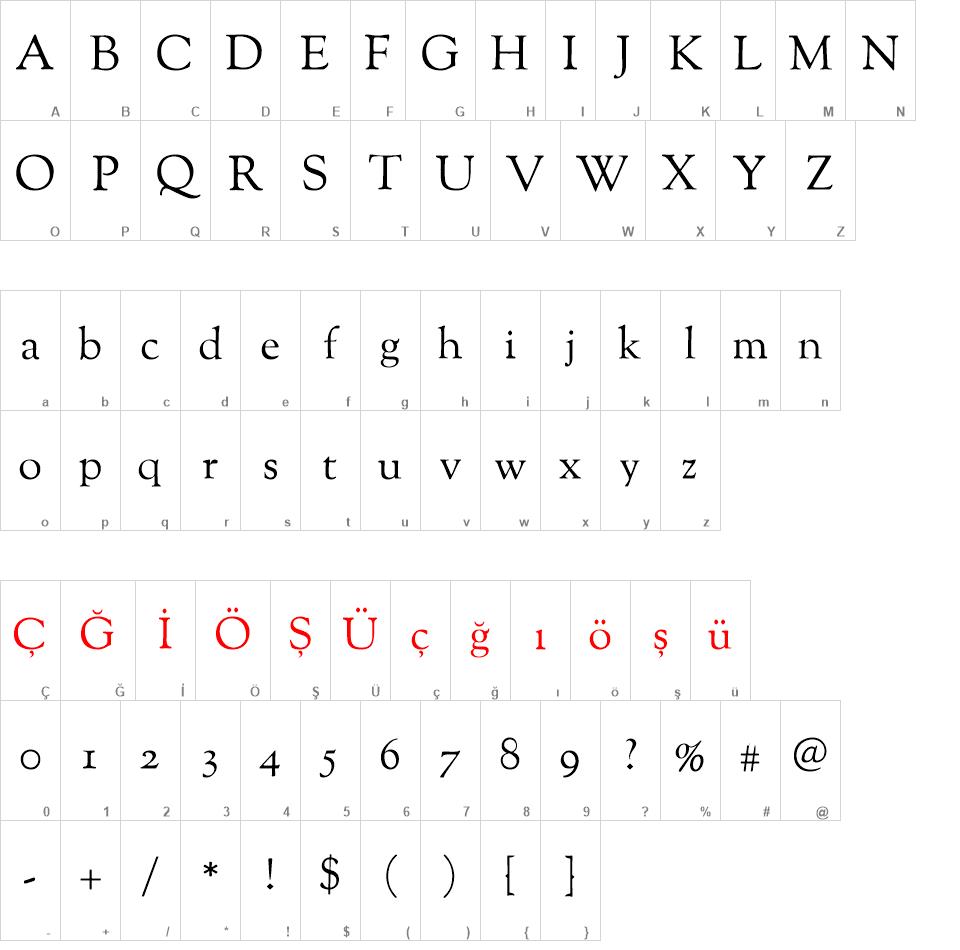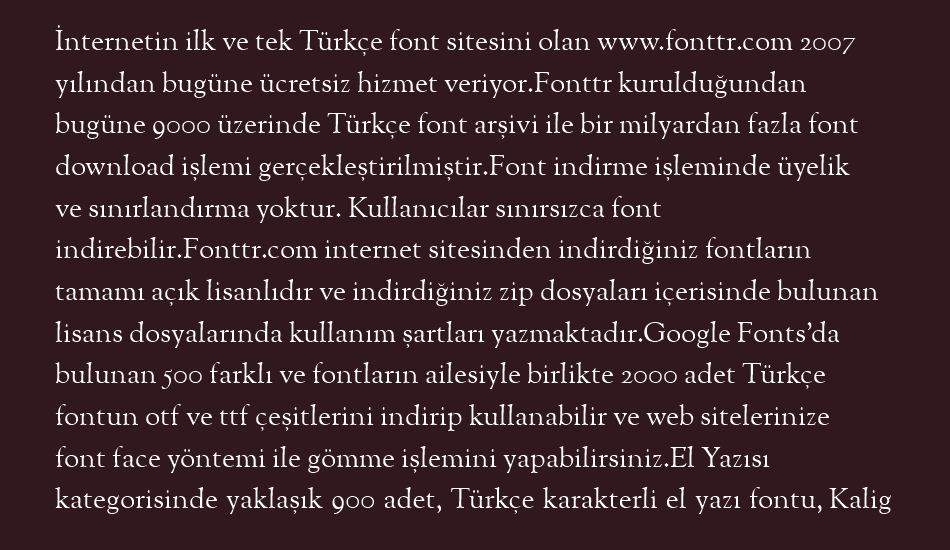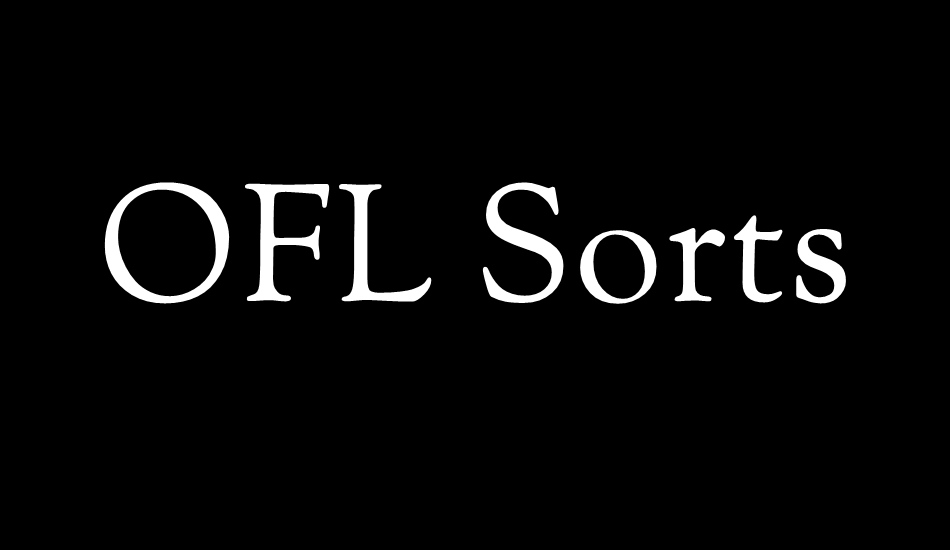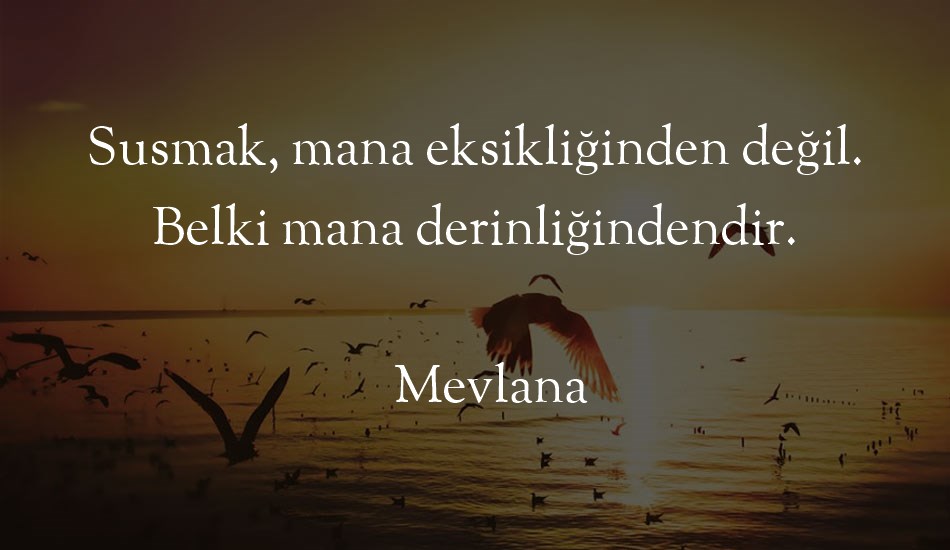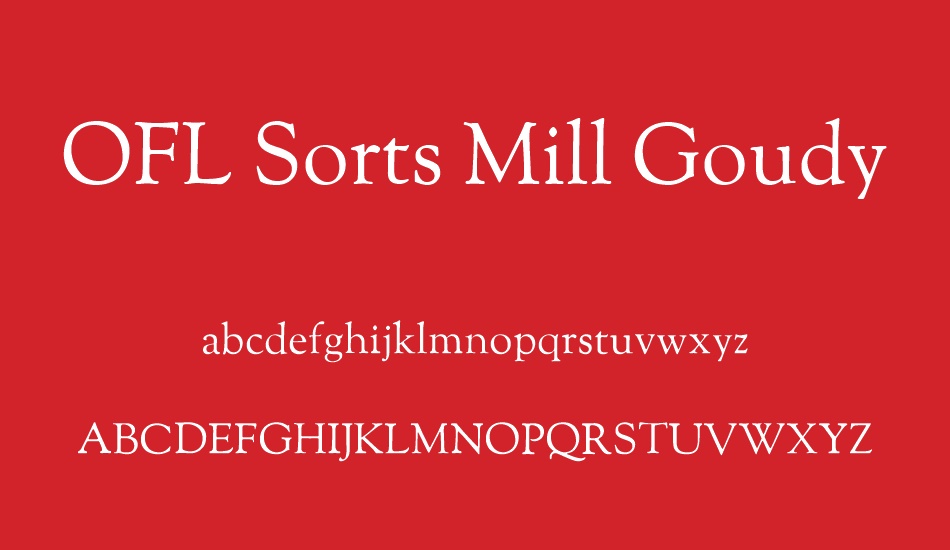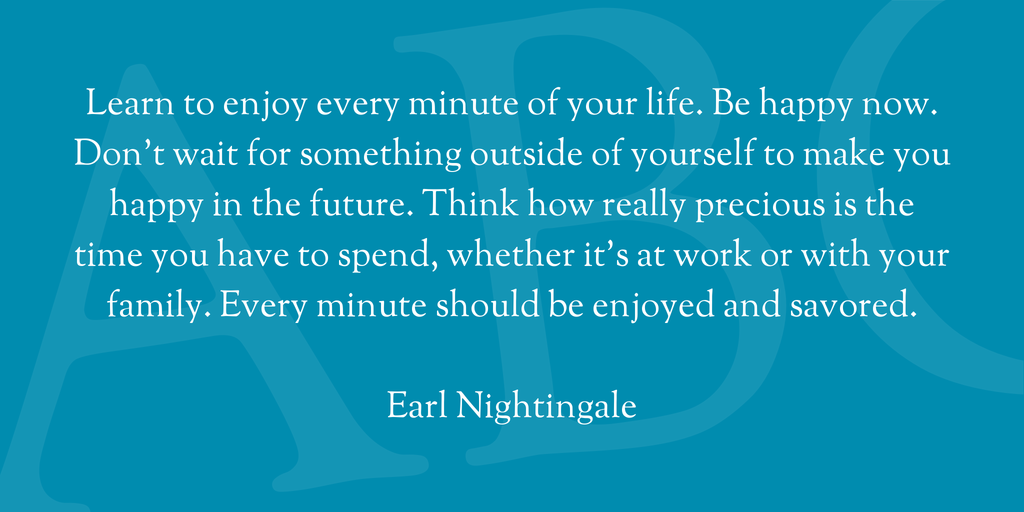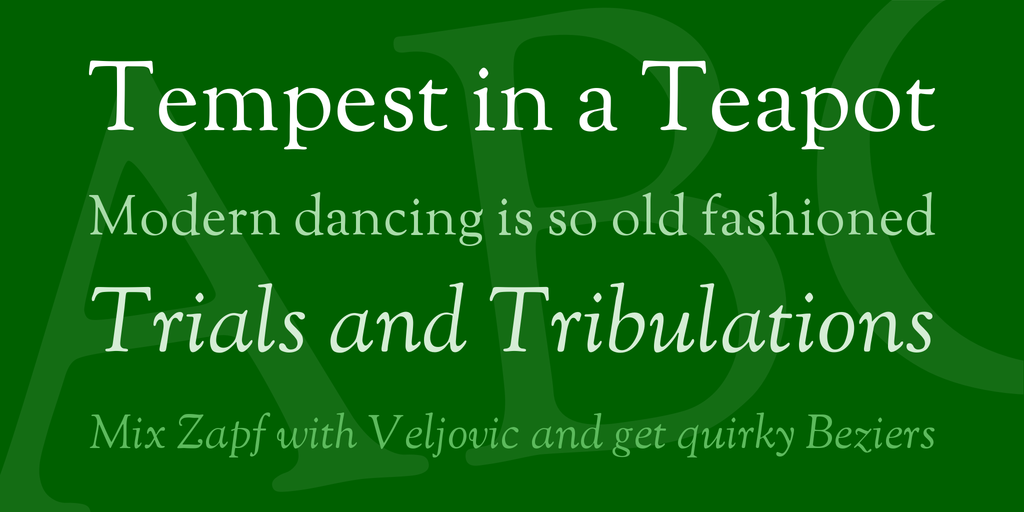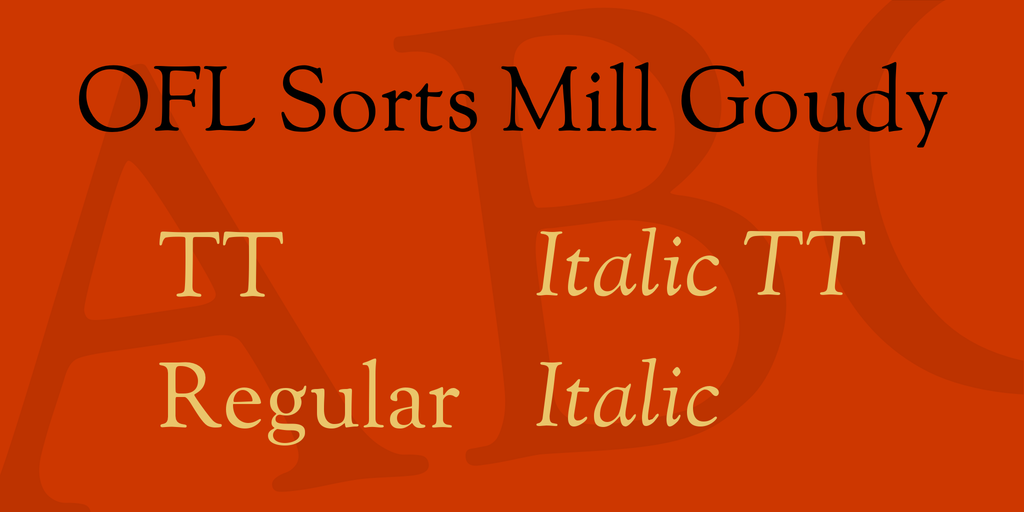
OFL Sorts Mill Goudy Font Family font
Frederic Goudy'nin 'Goudy Oldstyle''sinin Düzenli ve İtalik stillerle canlandırılması ve genişletilmiş Latin karakteri kapsaması.